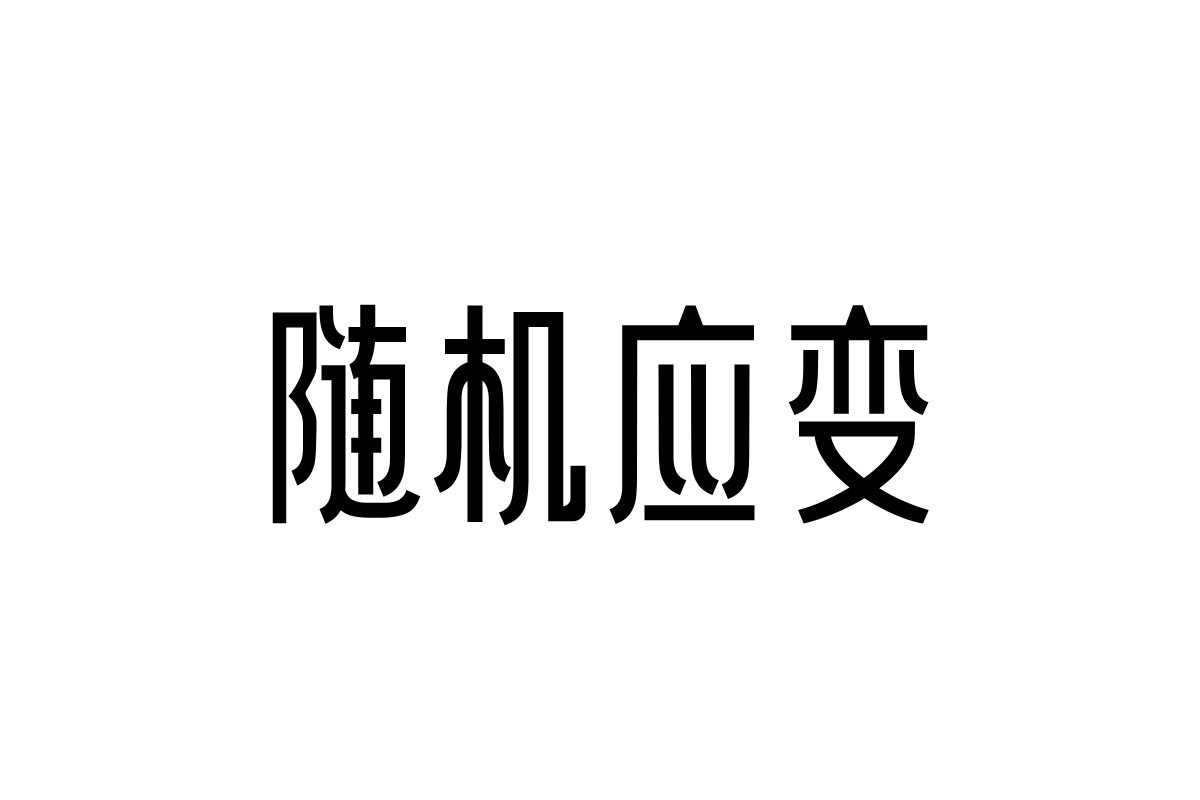
三极戟黑是一套具有强烈视觉冲击力的中文字体。它由设计师精心打造,旨在为各种应用和媒介提供独特而优雅的视觉体验。该字体以其独特的结构和风格,吸引了广泛的关注和喜爱。
三极戟黑的特点包括:
– 简洁而有力的笔画,使得文字在视觉上更加突出。
– 独特的结构设计,使得文字在排版时更具动感和立体感。
– 高对比度的色彩搭配,使得文字在背景中更加醒目。
– 适用于多种应用场景,如网页、广告、海报等。
总之,三极戟黑是一款具有创新性和实用性的中文字体,值得您尝试使用。